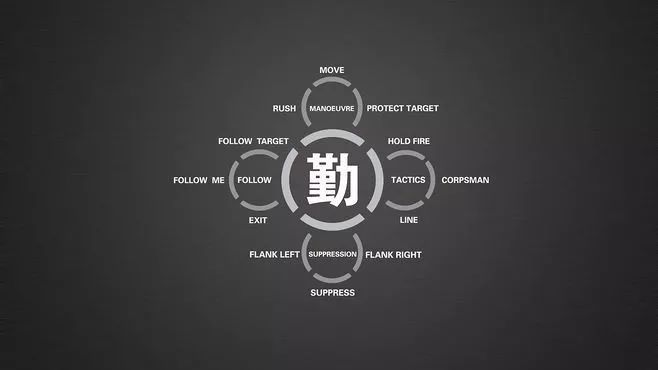
文字博大精深,从甲骨文到现在的汉字都展现着其丰富的内涵,而文字设计作为平面设计的基础元素,扮演着非常重要的角色。好的字体设计能让设计作品“活”起来。本文通过长期的设计实践,总结出以下几种常用的汉字设计方法:
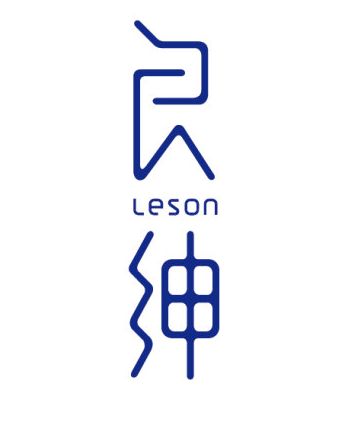
缺憾化设计
缺憾化的设计就是在汉字架构基础上减少部分笔画:
①将汉字“横”笔划缺省,“横”在汉字架构中有空间的平衡作用,缺省的设置会增加汉字的空间韵味。
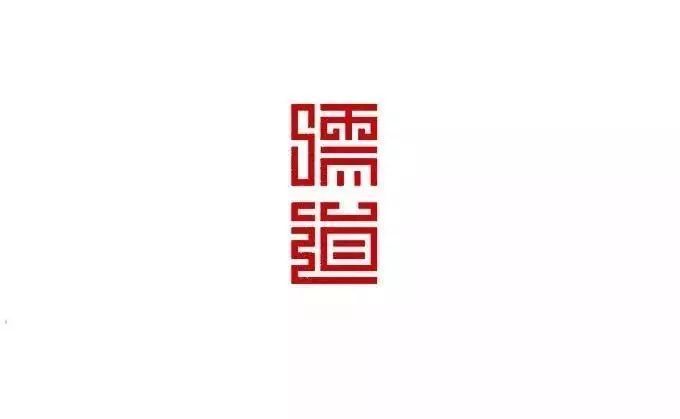
②将汉字竖”笔划缺省,“竖”在汉字中有树立稳定的作用,缺省的设置会使汉字增加不稳中求稳的韵味。
③将汉字“点”笔划缺省,取意“画龙点睛”的作用。
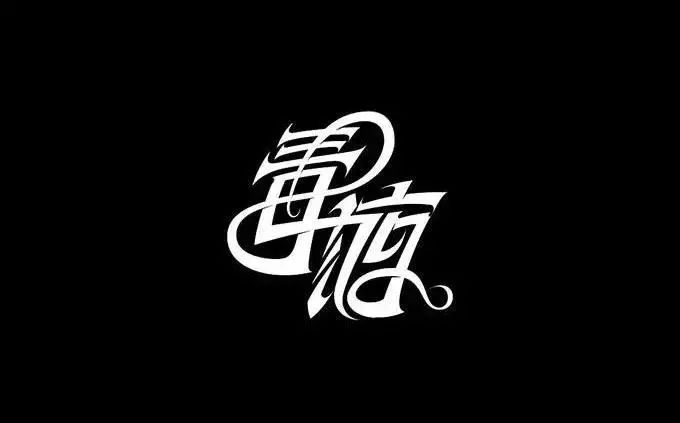
④将汉字“撇”或“捺”笔划缺省,能使汉字具有动感的韵味。
⑤将汉字“转折”笔划缺省等等。汉字的缺憾化设计给人以错觉,能够增加汉字的吸引力。
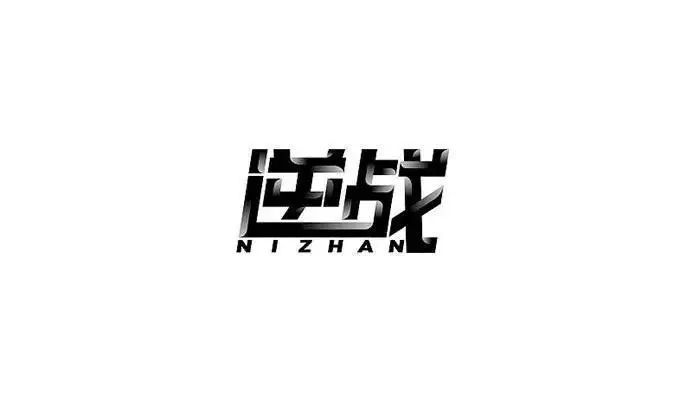
夸张化设计
①局部夸张。
用这种方法将汉字的部分加以变形,如将横变粗、将竖变细。这里面牵涉到一个“度”的问题,在具体设计过程中需要保持文字架构的整体性。
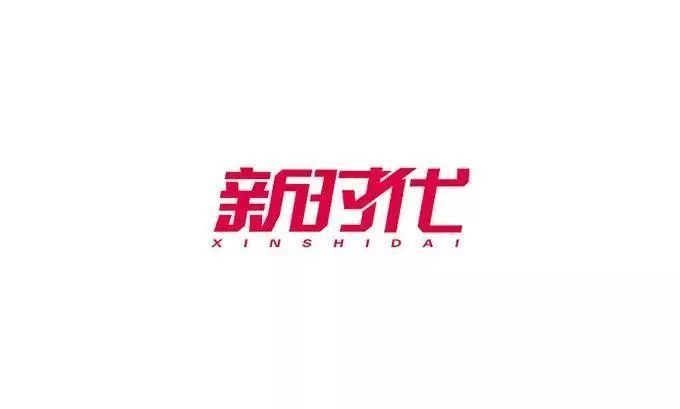
②整体夸张。
汉字本身以方块的形式存在,在设计过程中我们可以将方块字整体倾向于圆形化、三角形化、梯形化,上大下小、上小下大、上粗下细、上细下粗、上方下圆、上圆下方、外紧内松、外松内紧等。这种方法重点在于增加汉字本身的对比元素、增添活力。
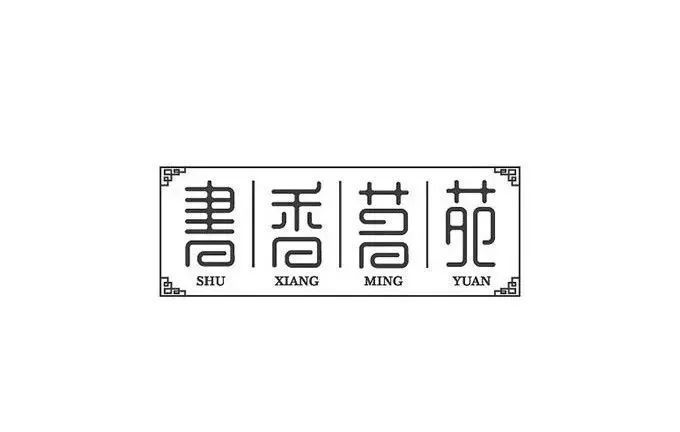
③嫁接。
将与汉字相关或不相关的元素,加到汉字的骨骼架构上,增加汉字的生动性,实现汉字意想不到的变化。
④软化。
这种方法颠覆了汉字方块字的稳定、坚硬的特点,整体设计使其倾向软化的特征,可以是局部或者整体的软化。这种方法无形中将方圆对比与刚柔对比相融合。
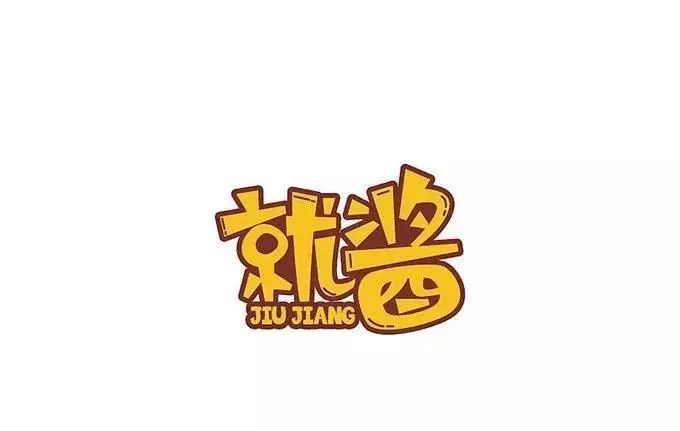
⑤强化棱角。
现有的汉字设计表现方法中,笔划转折处有方有圆,强化棱角可以将汉字棱角倾向于全方、全圆,或者四十五度角倾斜、椭圆转折等,形成汉字本身的一种节奏变化。
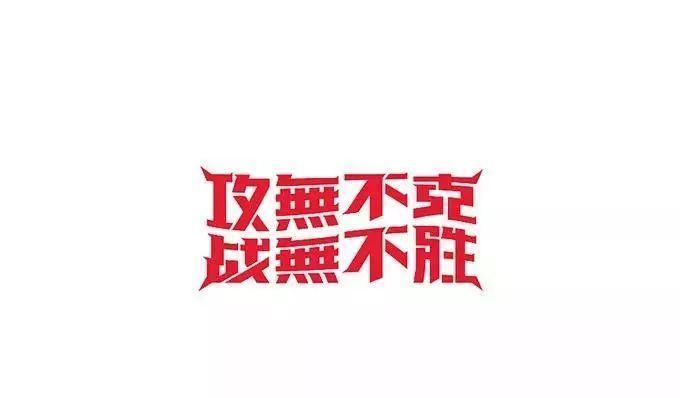
⑥打乱汉字构造。
汉字本身存在严谨的间架结构,实施这种设计方法就是将汉字本身的横竖点撇捺转折等元素的间距或搭配打乱,进行重置。这种方法在我们具体制作时候可分为两种,一种是将汉字笔画完全打散,但保持汉字的整理形态感;另一种是将结构打乱、笔划不变,存在形式不变。
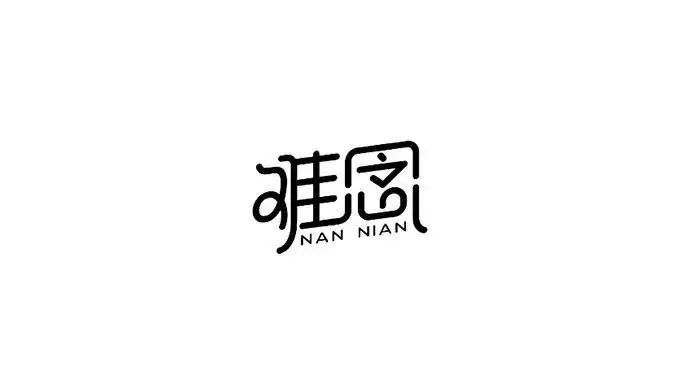
肌理化设计
这种设计方法主要侧重于汉字构成元素中填充物的变化。具体体现在两个方面:
①将汉字实施渐变的填充、分色段的填充、点的填充、线的填充、面的填充等。这几种手法的实施要保持汉字本身的结构特征,在汉字笔画的填充物上做“文章”。具体设计中汉字的边框保留与否根据实际需要而改变。
②将汉字的原字缩小进行填充。这种设计方法就是将汉字加以缩放至点、线的形式,然后填充到汉字的结构中去。
错位设计
汉字的一个非常明显的特征是结构严谨、稳重。错位设计就是改变这种呈现特征,有两个侧重点一是保持汉字整体的结构倾向,二是在此基础上进行适当打乱。这里总结出三种方法:
①汉字的局部或细节错位。如将横切断加以错位,将竖切断加以错位,或者将汉字在田字格中分成四份加以错位等,这种设计手法增加了汉字节奏中的流动感。在具体实施中还可以运用规则错位和不规则错位的方法,增加丰富的表现力。
②汉字的结构错位。这种设计方法侧重在结构的旋转、倾斜后的错位变化。
③设计过程在汉字的整体架构中结合,构成形式中的对比、聚散、疏密、渐变等关系来体现,目的在于增加汉字的空间塑造感和丰富表现力。在一个汉字中体现聚散本身是对汉字固有架构的再塑造,“破坏”方法在汉字设计方法中也有很多设计师在尝试,就如上面所列“缺憾化设计”方法,构成化设计方法是改变结构,融进显著的聚散、疏密、渐变等,可以使汉字设计的生动性增强。
图形化设计
汉字的体形是由汉字的笔画造型及间架结构组成,具有一定的抽象纹样装饰美的象征意义。将汉字笔画元素进行大小、疏密、粗细、明暗、虚实、空间等变化后组成的图形置于具体的图像造型之中,使图像更具有装饰纹样的视觉美。汉字元素可以曲线的、直线的、打散重组的、随意排列的,置于具体的图像之中,从而获得各种各样的表现形式。
空间化设计
空间往被理解为抽象的、不可视的、难以感受和琢磨,只能想象的概念,而汉字的字形结构、偏旁部首的整体链接和完全封闭都可以用来实现空间的形式。空间化设计方法可以通过笔画转折的变化、抽象空间形式、具象空间形式、点线面元素的挪移来实现。